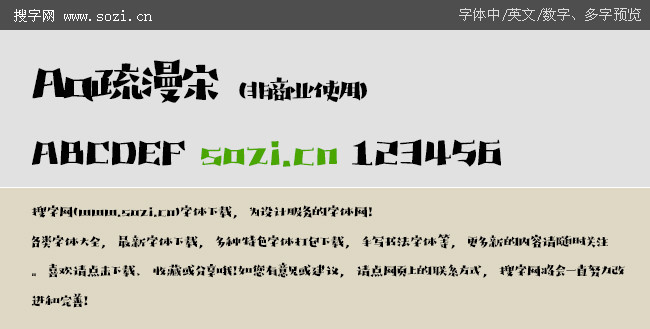
Aa疏漫宋
搜字網(wǎng)給大家提供一款A(yù)a疏漫宋(非商業(yè)使用)中文字體下載,該字體是一款非常俏皮可愛的宋體藝術(shù)字體,該字體在宋體的基礎(chǔ)上,對(duì)字型筆畫進(jìn)行局部加寬處理,使字體字型隨意、散漫、有規(guī)律,具有很好的視覺感,適合書裝設(shè)計(jì)、包裝、海報(bào)設(shè)計(jì)等應(yīng)用(此字體為個(gè)人非商用版,商用可以聯(lián)系QQ:1006760504)。